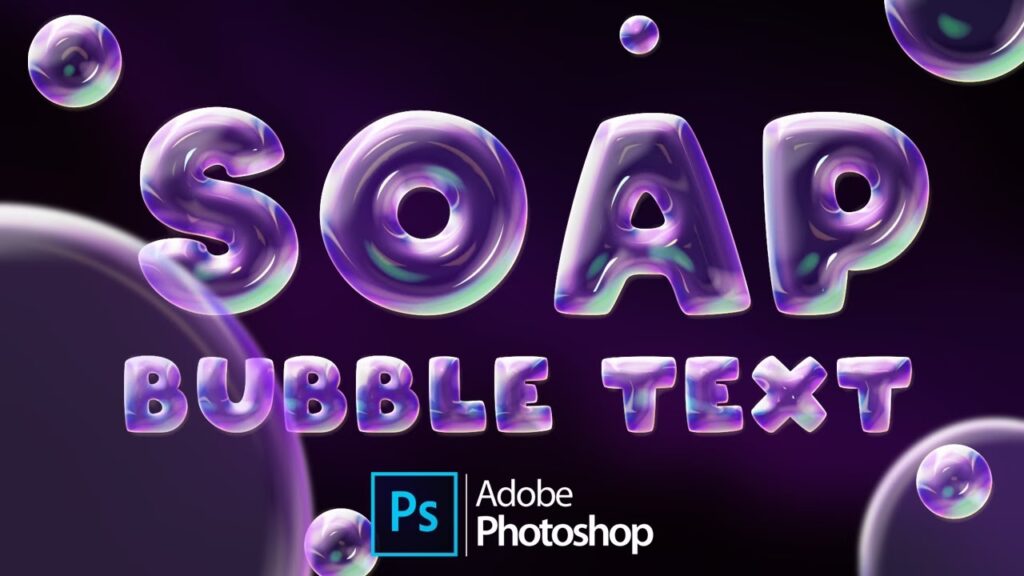
Som grafiske designere er vi altid på udkig efter sjove, legesyge skrifttyper, der kan tilføre en følelse af glæde og finurlighed til vores projekter. Og i 2024 er bobleskrifttyper – eller 'bubble fonts' – dukket op overalt, fra branding til emballage til t-shirt designs. De forventes at fortsætte deres 'poppende' popularitet ind i 2025.
Bobleskrifttyper er præcis, hvad de lyder som – skrifttyper med runde, boblede bogstaver, ofte med en håndskrevet eller illustreret stil. De har en livlig, hoppende kvalitet, der føles optimistisk og energisk. I denne artikel dykker vi dybt ned i de bedste bobleskrifttyper, du kan prøve, og udforsker, hvad der giver dem deres sjove, legesyge vibe, hvor de bedst bruges (og hvor de skal undgås), fantastiske alternativer, og svar på almindelige spørgsmål.
De mest populære bobleskrifttyper i 2024/2025
Lad os se det i øjnene, ikke alle bobleskrifttyper er skabt lige. Derfor har vi samlet en liste over vores favoritter lige nu:
- El Mojo: En sød, legesyg sans serif skrifttype, perfekt til fødevareemballage, børnebøger og lyse, sjove designs. Dens boblede bogstavformer har et venligt, afrundet udseende.
- Bubble Boom: Har en cool graffiti-inspireret stil med dristige, kantede bogstavformer. Den ville være fantastisk til urban streetwear designs, hiphop albumcovers eller ungdomsbrands, der ønsker et trendy look.
- Bubble Mint: En finurlig, legesyg script skrifttype med en sød, boblende stil. Den ville være perfekt til fødselsdagskort, emballage, ungdomsbrands eller til at tilføje et håndlavet præg til designs.
- Sugar Bubble: Har en sød, dristig, boblende stil. Dens legesyge vibe gør den perfekt til kunst, håndværk, citater, plakater, logoer eller alt, hvor du ønsker en charmerende, venlig tone.
- Black Bubbles: En elegant display skrifttype med smukke, udsmykkede sorte bogstavformer, der indeholder delikate hvide bobler inde i hver enkelt. Den har et blødt, delikat udseende, perfekt til invitationer.
- Bubble Shine: En munter, venlig display skrifttype. Dens glatte, afrundede bogstavformer kombineret med højdepunkter omkring hver enkelt giver den et lyst, legesyg udseende, fantastisk til børnebrands.
- JellyBelly: En sød, vrikkende display skrifttype med ujævne, hoppende bogstavformer, der minder om farverigt slik. Den har et lyst, sjovt, ungdommeligt udseende.
- Blopy: En boblende retro display skrifttype med let ujævne bogstavformer, der skaber legesyg tekstur. Dens afrundede stil gør den perfekt til store, iøjnefaldende overskrifter og titler.
- Frisky Puppy: En glad, smilende display skrifttype. Dens søde hundekarakterformer skaber en varm, venlig tone, perfekt til børneprodukter, Youtube thumbnails, t-shirts og meget mere.
- Blobber: En legesyg, venlig display skrifttype med søde, boblede bogstavformer. Dens bløde former og ujævne stil skaber en varm, indbydende tone, fantastisk til børnebrands og tegneserieagtige designs.
- Rubber Duck: Har en sød, ballonlignende stil med glatte, afrundede bogstavformer. Dens venlige udseende er perfekt til børneprodukter, legetøj, bøger, papirvarer og alt, der ønsker en varm, legesyg tone.
- Sunspot: Har en munter, ballon-dyr-stil. Dens hoppende bogstavformer og højdepunkter omkring hver enkelt giver den en varm, indbydende tone, perfekt til legesyge børnebrands og legetøjsemballage.
- Valoon: En sød, venlig display skrifttype. Den har en let afrundet stil, der minder om puffy balloner, hvilket skaber en munter, optimistisk tone, perfekt til ungdomsbrands.
- Shine Bubble: En dristig, boblende display skrifttype. Den findes i fyldte og outline versioner, fantastisk til at tilføje et farverigt, legesyg præg til logoer, overskrifter, brandingprojekter og meget mere.
- Tijuf: Har en unik, legesyg display skrifttype stil med farverige, ujævne bogstavformer. Den har et sjovt, hoppende udseende, perfekt til at tilføje energi og personlighed til overskrifter og titler.
- Kembol: En finurlig display skrifttype med et håndtegnet look. Dens hoppende, animerede stil skaber visuel interesse, perfekt til at tilføje energi og unikhed til overskrifter, logoer og titler.
- KIND HUMAN: En sød, venlig håndskrevet skrifttype med glatte kanter og subtile højdepunkter omkring hvert bogstav, der giver den en boblende stil. Den er perfekt til kunst, håndværk, logoer, citater og mere.
- Kooky Cloud: En ekstra dristig, boblende display skrifttype. Dens høje højde og glatte, men finurlige bogstavformer giver den masser af personlighed, perfekt til iøjnefaldende overskrifter og logoer.
- Pool Noodle: Har en retro boble bogstav stil, perfekt til at fange 90'ernes nostalgi. Dens afrundede, hoppende bogstavformer er fantastiske til designs, der ønsker en sød, doodle-lignende tone med masser af personlighed.
- Bubblegum Font Duo: Inkluderer script og dekorative stilarter. Begge har legesyge, hoppende bogstavformer, der er perfekte til at parre sammen for at skabe en sjov, ungdommelig tone til invitationer, branding, babyprodukter og mere.
- Tubbs: En fed, boblende skrifttype, perfekt til at tilføje et sødt, legesyg præg til ethvert projekt. Dens bløde, puffy bogstavformer har en venlig varme, der hjælper med at formidle optimistiske, positive følelser.
- Wildside: Har en sjov, boblende håndskrevet stil med glatte kanter. Den kan lægges i lag for masser af variation, perfekt til skjorter, branding, logoer, sociale medieopslag og alt, der ønsker en legesyg tone.
- Cool Vibes: Har en munter, boblende retro stil. Kombinationen af glatte og teksturerede bogstavformer giver den et håndlavet udseende, perfekt til skjortedesigns, branding, SVG-filer og mere.
- Baby Balloon: En lagdelt skrifttype med 3 versioner – regular, outline og inner shadow. De afrundede bogstavformer ligner skinnende balloner, fantastisk til børnedesigns, fødselsdagskort, munter branding og mere.
- Bubbles: Har en sød, legesyg håndskrevet stil. De ujævne bogstavformer giver den masser af personlighed, perfekt til emballage, citater, lykønskningskort, invitationer, planlæggere og alt sjovt.
- Holiday Journey: En dristig, boblende skrifttype, der kan lægges i lag for masser af variation. Fantastisk til lykønskningskort, Instagram-opslag, citater og alt, hvor du ønsker legesyge, hoppende bogstavformer fulde af energi.
- Bubble Text 3D Letters: Dette sæt indeholder dristige, farverige boble bogstav PNG'er, perfekte til festinvitationer, meddelelser, bryllupsdesigns, webgrafik og ethvert projekt, der ønsker en sjov, legesyg stil.
- Peanut Donuts: Har en boblende retro stil, der minder om skilte fra soda shops. Dens legesyge, nostalgiske vibe er perfekt til emballage, plakater, merchandise, citater, overskrifter og alt, hvor du ønsker et sjovt, vintage udseende.
- Splash: En munter håndskrevet skrifttype, der kan have solide eller skinnende bogstavformer. Sjov til logoer, branding, SVG-filer, skjorter, klistermærker og alt, hvor du ønsker et personligt, håndlavet look.
- Joypops: En sød, venlig håndskrevet skrifttype med subtil bounce i bogstavformerne, der minder om bobler. Fantastisk til logoer, branding, undertekster og til at tilføje personlighed med dens legesyge stil.
- Bubble: En farverig, munter display skrifttype, skabt til at efterligne den lysreflekterende tekstur af ægte sæbebobler. Perfekt til at tilføje lyse, iøjnefaldende overskrifter og titler med en legesyg stil.
- Real Cool: En stilfuld, retro-inspireret bobleskrifttype med en 70'er vibe. Dens kurvede og legesyge bogstavformer bringer en sjov, afslappet æstetik til ethvert designprojekt, hvilket gør den perfekt til plakater, branding og sociale mediegrafik.
- Super Shiny Pink 3D Letters: Slip din kreativitet løs med denne blændende pakke af super skinnende pink 3D-bogstaver! Med alsidige PNG-karakterer og en matchende SVG Bitmap-skrifttype lader dette sæt dig skabe iøjnefaldende designs i forskellige software, med fleksibilitet til at justere farver og tilføje realistiske skygger for maksimal visuel effekt.
- Double Bubble: Dyk ned i finurlig typografi med Double Bubble, en legesyg display skrifttype, der bringer tekst til live med sine fluffy, flydende bogstavformer. Denne charmerende skrifttype, tilgængelig i outline og regular versioner, vækker nostalgiske barndomsminder og tilføjer et dejligt, iøjnefaldende flair til ethvert designprojekt, fra plakater til hjemmesider.
Hvad gør bobleskrifttyper så legesyge?
Bobleskrifttyper får deres legesyge, hoppende personlighed fra et par nøglekarakteristika:
Afrundede, overopblæste bogstavformer
For det første er der selvfølgelig de runde former. Bobleskrifttyper har bogstaver, der er formet som bobler – runde og oppustede på alle sider. Dette giver bogstavformerne den bløde, glatte, rullende form, der minder om faktiske bobler.
Overopblæsningen skaber bogstaver, der føles dejligt fyldige, som om de næsten kunne flyde væk. Den bløde rundhed føles indbydende og ikke-truende.
Naturlig ujævnhed
De fleste bobleskrifttyper har også naturlig ujævnhed mellem bogstaverne. Deres størrelser, former og grundlinjer varierer, ligesom naturlig håndskrift. Dette giver et organisk, menneskeligt præg.
Lighederne med hoppende bobler fortsætter i den vertikale afstand. Bogstaverne bevæger sig op og ned med variation, hvilket fremkalder den samme flydende, hoppende bevægelse.
Sjove teksturer og skygger
Endelig tilføjer bobleskrifttyper ofte ekstra elementer som farverige teksturer eller skygger. Disse legesyge udsmykninger komplementerer de venlige runde bogstavformer. Kombinationen skaber en livlig, animeret effekt.
Alt i alt er disse træk – runde former, ujævne grundlinjer, udsmykninger – det, der definerer den legesyge attitude hos en bobleskrifttype.
Hvor kan du bruge bobleskrifttyper?
Nu hvor vi forstår, hvad der driver bobleskrifttyper, hvor kan vi så faktisk bruge dem i designs? Deres legesyge vibe gør bobleskrifttyper til et alsidigt valg:
Branding
Bobleskrifttyper er et fantastisk valg for brands, der retter sig mod yngre målgrupper eller promoverer leg, glæde og lethed. For eksempel børnebrands, legetøjsbutikker, slikbutikker, familieunderholdningscentre, karnevaler, zoologiske haver, akvarier, fødselsdagsfester eller baby/børneprodukter.
Ethvert brand, der skal føles optimistisk, livligt og energisk, kan drage fordel af en passende bobleskrifttype i deres visuelle identitet.
Emballage
På samme måde er bobleskrifttyper sjove, engagerende valg til ungdomsorienteret produktemballage. Især børnemad, legetøj, kunsthåndværk eller festartikler.
Beklædning og merchandise
Bobleskrifttyper tilføjer også masser af personlighed på t-shirts, hatte, plakater, krus, knapper, klistermærker og andet merchandise. De får designs til at føles mere livlige og fanger øjet. Fantastisk til bands, YouTube-personligheder eller brands, der retter sig mod yngre grupper.
Invitationer
Til fødselsdagsfester, babyshower, bryllupper eller andre fejringer sætter en legesyg bobleskrifttype den rette livlige tone.
Digitale designs
Bobleskrifttyper fanger også opmærksomhed online. Deres venlige rundhed hjælper med at vise vigtig information tydeligt på skærme. Fantastisk til hjemmesider, mobilapps, bannerannoncer, sociale medieopslag, e-mail nyhedsbreve, YouTube-videoer eller brugergrænsefladeelementer.
Hvor skal du undgå bobleskrifttyper?
Selvom bobleskrifttyper er fantastiske til mange anvendelser, er der visse situationer, hvor de måske ikke er det bedste valg. Nemlig i sammenhænge, der kræver:
Professionalisme/Alvor
I formelle virksomheds-, juridiske, medicinske, finansielle sammenhænge vil bobleskrifttyper sandsynligvis føles for legesyge og mindske den opfattede professionalisme. I disse tilfælde skal du vælge autoritative seriffer i stedet, der føles polerede, traditionelle og sofistikerede.
Klarhed
I designs, hvor hurtig informationsabsorption er kritisk – datavisualiseringer, vejskilte, tekniske manualer eller nødinstruktioner – optimerer standard humanistiske sans seriffer klarheden. Bobleskrifttyper kan muligvis bremse forståelsen en smule. Hold dig til simple, læselige valg i stedet.
Tradition
Til designs, der fejrer arv, historie eller formidler lang levetid, føles standard serif-skrifttyper mere passende og tidløse. Museer, etablerede virksomheder, historiske selskaber vælger ofte klassiske, velkendte seriffer.
Så selvom de er livlige og sjove til et hav af anvendelser, skal du overveje konteksten grundigt, når du beslutter, om en bobleskrifttype giver mening. Deres legesyge kan underminere visse æstetikker eller budskaber, der kræver nøgternhed.
Sådan vælger du den perfekte bobleskrifttype
For at vælge en fremragende bobleskrifttype, der matcher dine behov, skal du først overveje:
Stemning og tone
Overvej den ønskede stemning. Drømmeagtig? Retro? Luksuriøs? Munter? Match æstetiske kvaliteter. En slank, raffineret bobleskrifttype formidler elegance. En tekstureret, skyggefuld bobleskrifttype føles drømmeagtig. Identificer adjektiver, der beskriver den ideelle vibe, og find derefter skrifttyper, der udtrykker disse træk.
Målgruppe
Tag højde for målgruppen og deres visuelle stilpræferencer. Yngre målgrupper vil sandsynligvis byde legesyge bobleskrifttyper velkommen, der passer til deres alder. Mere modne grupper kan opfatte overlyse bobleskrifttyper som mindre seriøse eller raffinerede.
Medium
Overvej, hvor og hvordan designs vil blive set – digitalt eller print? Lille eller stor anvendelse? Sørg for, at skrifttypen fungerer ved de tilsigtede størrelser og overføres rent mellem medieformater. Test bobleskrifttypeprint ved små størrelser for at bekræfte læsbarhed. Gennemse på faktiske digitale skærme for at evaluere læsbarhed.
Parring
Når du kombinerer bobleskrifttyper med andre skrifttyper, skal du sikre harmoniske relationer. At parre en livlig boble script med en dristig slab serif kan føles usammenhængende. Men at kombinere med en ren sans-serif eller komplementerende script flyder godt. Vær opmærksom på skrifttypekombinationer.
Med stemning, målgruppe, medium og parringer i tankerne bliver det intuitivt at matche en passende bobleskrifttype!
Fantastiske alternativer til bobleskrifttyper
Mens bobleskrifttyper i sig selv tilfører livlig energi til designs, kan alternativer også give den legesyge, venlige appel.
Nogle topmuligheder inkluderer:
Legesyge Script Skrifttyper
Scripts som Dancing Script, Sacramento eller La Belle Aurore har de flydende, hoppende bevægelser, der minder om bobleskrifttyper. Disse legesyge scripts fanger den følelse af glæde med fritflydende bogstavformer.
Venlige Håndskrevne Skrifttyper
Håndskrevne skrifttyper som Brothers, Whisper eller Homemade Apple giver også personlig, indbydende varme, ideel til uformelle sammenhænge. Deres uperfekte former føles autentiske.
Kunstneriske Display Skrifttyper
For en dristig, iøjnefaldende effekt med personlighed fungerer display skrifttyper som Luckiest Guy, Coolsville eller Hopsctoch magisk. Deres kunstneriske bogstavformer fanger opmærksomhed, samtidig med at de formidler munterhed.
Så at genskabe bobleskrifttypers legesyge positivitet er også muligt med scripts, håndskrevne og kunstneriske displays!
Ofte stillede spørgsmål om bobleskrifttyper
Lad os afslutte med at besvare nogle almindelige spørgsmål om bobleskrifttyper:
Hvilken skrifttype ligner en boble?
Skrifttyper med runde, oppustede bogstavformer og livlig energi som Luckiest Guy, Balloon Anarchy eller Homespun minder meget om bobleskrifttyper. Legesyge scripts fanger også hoppende bevægelser.
Hvad kaldes bobleskrifttypen?
Mens der ikke findes en endegyldig "bobleskrifttype", fanger muligheder som Bubbleboddy Neue – med runde, vrikkende bogstavformer – eller Denver – med farverige boble bogstaver – navnet bogstaveligt talt. Navne refererer normalt direkte til bobler.
Findes der en bobleskrifttype i Word?
Ja! Words standard skrifttyper inkluderer Baskerville Old Face, som har afrundede klatserriffer, der minder lidt om bobler. Også Lucida Handwriting og Jokerman med runde, hoppende bogstaver. Ikke ægte bobleskrifttyper, men tætte alternativer, der er indbygget i Word.
Hvad er den mest boblende skrifttype?
Skrifttyper som Bubbleboddy Neue, Denver eller Bulbobble har ultra-runde bogstaver med naturlig ujævnhed mellem bogstavformerne for særligt boblende, animerede designs. Disse fanger teksturen og bevægelsen af faktiske bobler for maksimal legesyge.
Bobleskrifttyper indånder glæde og finurlighed i designs, der skal opløfte publikum. Deres livlige runde former sikrer, at positivitet og munterhed bobler op til overfladen!
Så prøv nogle af disse sensationelle bobleskrifttyper i dine egne projekter. Brugt gennemtænkt skaber de mindeværdige designs, der helt sikkert får seerne til at smile.